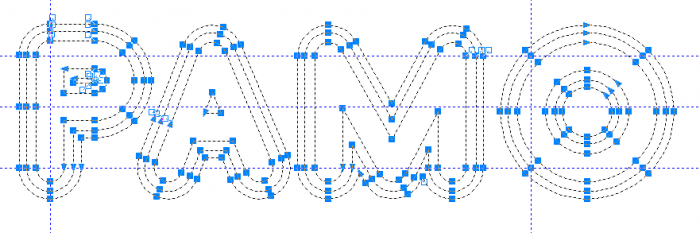
Welche Schrift ist das? (PAMO)
Ich suche folgende Schriftart. Leider ist die Schrift vektorisiert worden.
Erinnert mich an den Aldi Norwegens …
Hab leider keinen Schriftnamen dazu, aber vielleicht hilft’s ja weiter ;-)
Ich habe das Bild „REMA 1000“ genommen und mit dem Kanalmixer so auf S/W gesetzt das die rote Outline verschwindet. Annahme: Es wurde eine normale Outline genommen und umgearbeitet. So finde ich am schnellsten die dazu gehörige Basisschrift. Hier mal die nächste Schrift:
Wurde für das Logo PALO die Hiruko Outline oder eine ähnliche Schrift als Basis genommen und umgearbeitet?
Irgendwas dabei? Die Aldi-Norwegen-Schrift ist nicht zu finden ... Schade ... Hilft das jetzt etwas weiter?
Habe nun eine sehr ähnliche Schrift gefunden, mit der ich den Job bearbeiten kann.
Ich habe habe die Schrift «Hiruko» genommen und den neuen Schriftzug mit ein wenig Tüfteln nachgesetzt.
Die Schrift «Hiruko» hatte ich bereits auf meinem System gespeichert, deswegen entschied ich mich für diesen Weg.
Wenn es mit dieser Schrift nicht funktioniert hätte, wäre ich auf die Frankfurter Inline ausgewichen.
Gerade bei Logos sollte man sich, meiner Erfahrung nach, oft besser die Frage stellen: "wie schnell lässt sich das freiu nachzeichnen" statt nach der Schrift zu fahnden. Das Logo hab ich testweiose mal nachgezeichnet, hat gerade 3 Minuten gedauert.
Und da Logos nicht selten auch so gebaut werden, wird wohl die schrift nicht vektorisiert sdein, sondern die Vektoren nicht zur Schrift gemacht worden sein.